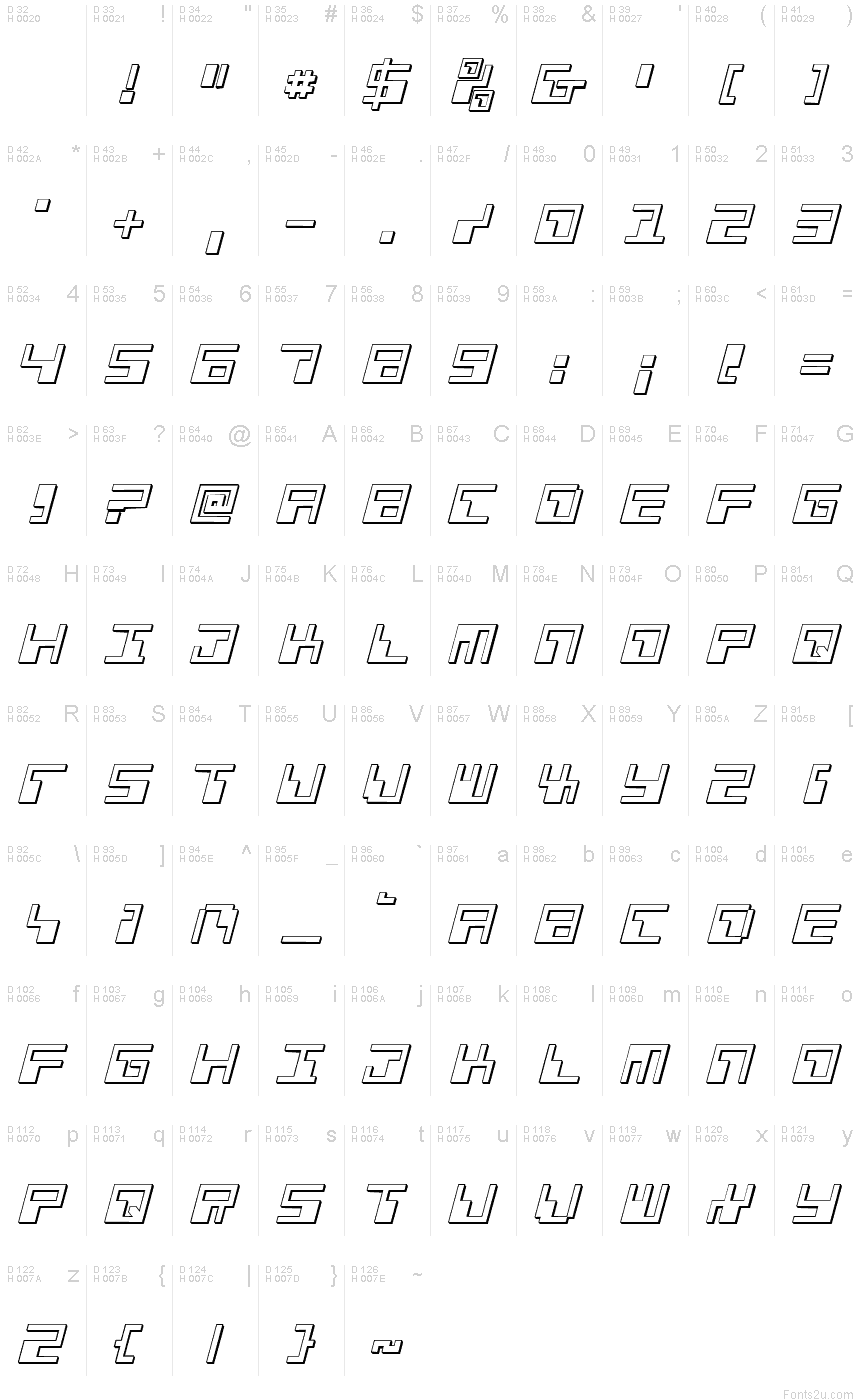
Phaser Bank 3D Italic od Iconian Fonts to darmowy, futurystyczny, trójwymiarowy krój pisma typu display, który oddaje wyrazisty, kanciasty klimat napisów sci-fi z ery automatów arcade. Litery pochylają się do przodu w szerokich, kwadratowych formach, a przesunięty kontur tworzy efekt fazowanej głębi, nadając krojowi szybki, mechaniczny charakter.
Świetnie sprawdza się w logotypach gier, nagłówkach plakatów, wizerunkach marek technologicznych, planszach tytułowych i okładkach, gdzie potrzebna jest darmowa czcionka z dynamiką, ale bez chaosu. Ponieważ kształty pozostają wyraziste i geometryczne nawet przy efekcie 3D, krój pasuje też do krótkich znaków słownych i monogramów, które mają wyróżniać się w stylu retro-future, a nie w stonowanym, korporacyjnym tonie.